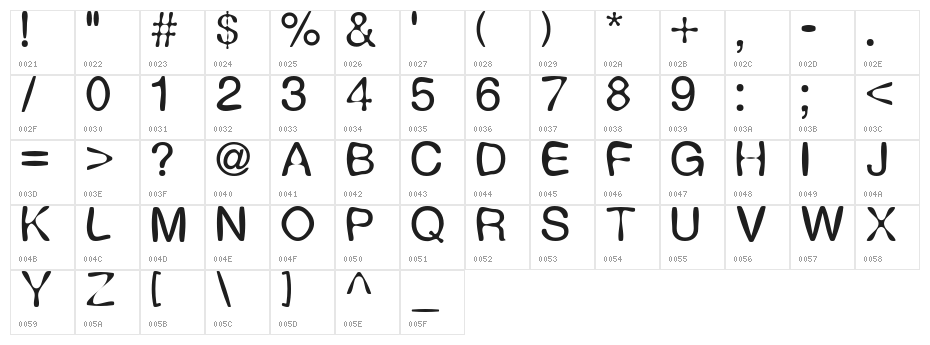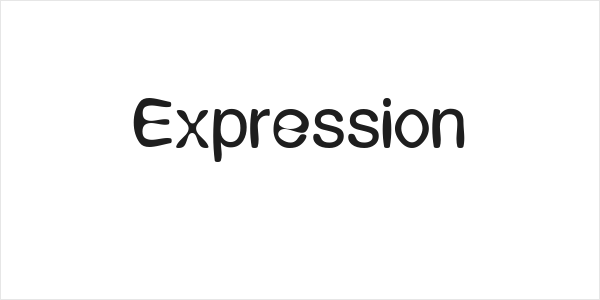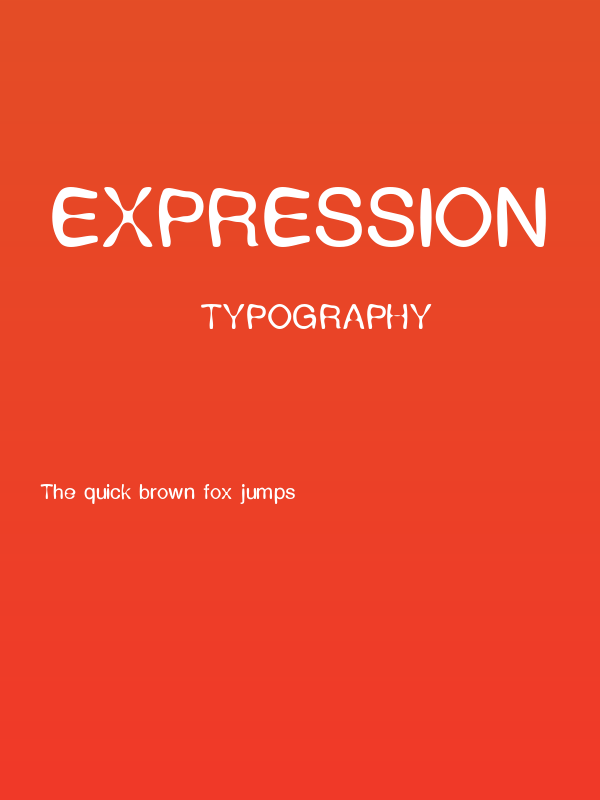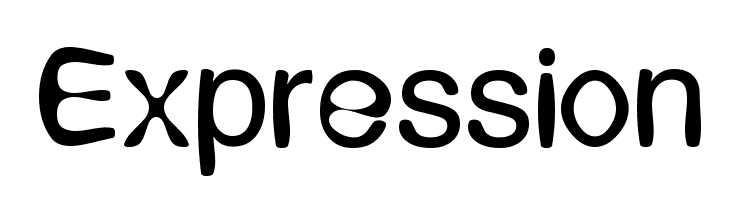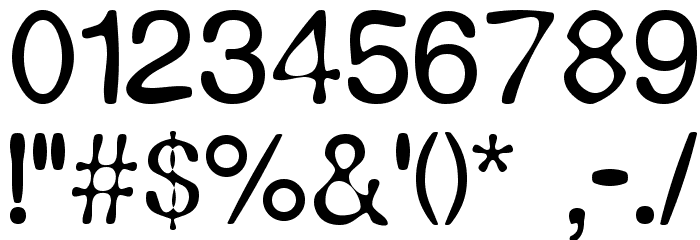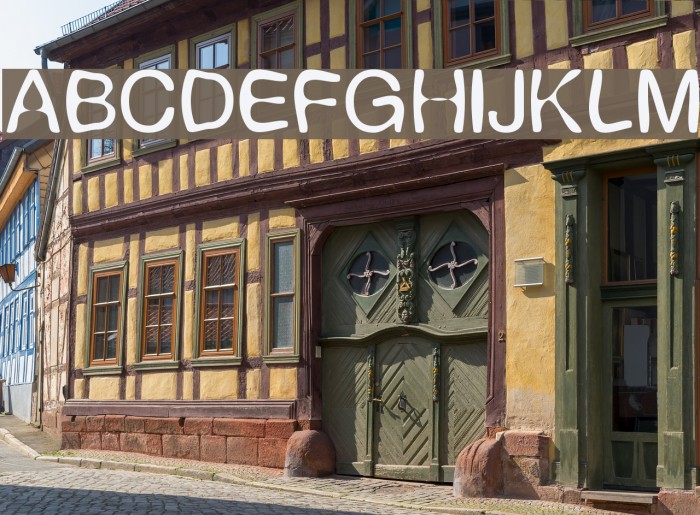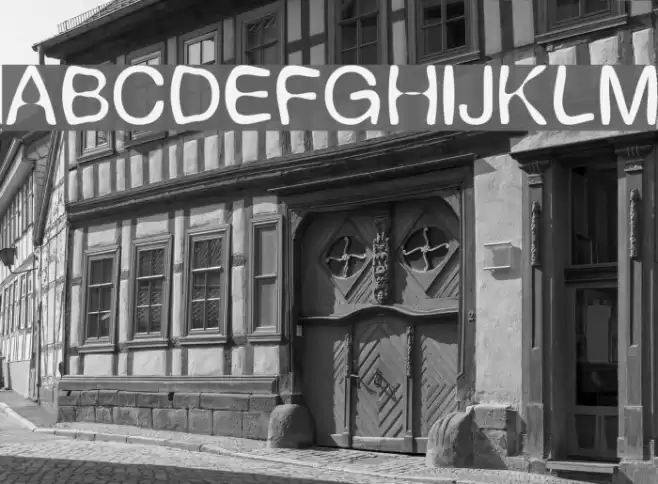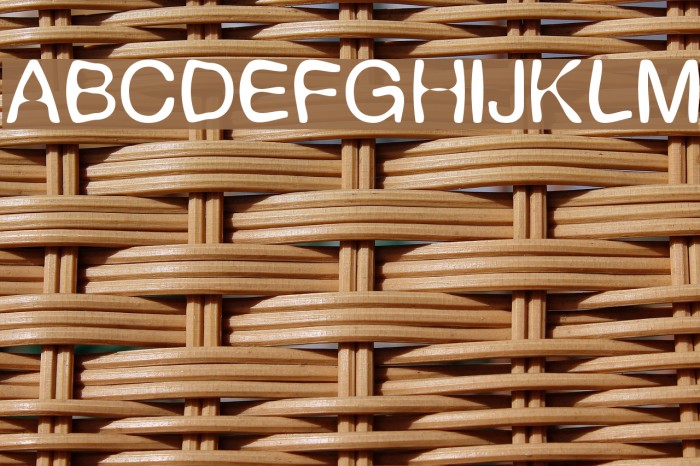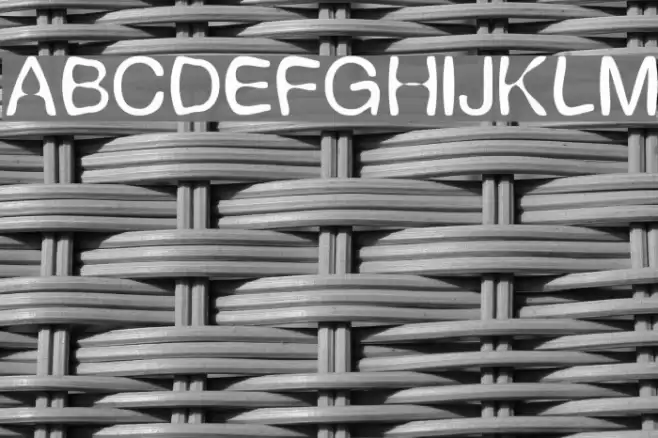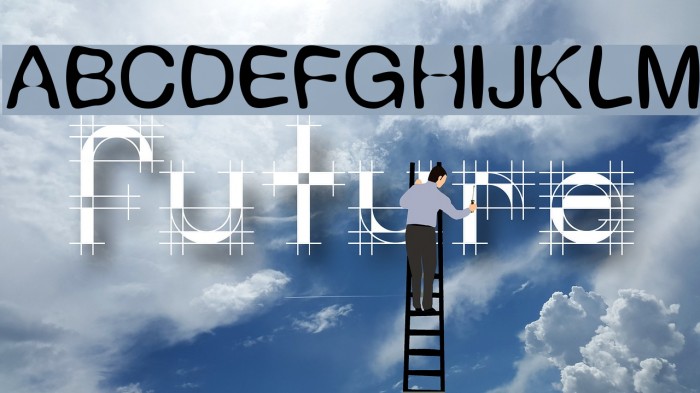
Expression Font
| Общий стиль | Playful, Whimsical |
| Рекомендуемые проекты | Ideal for children's books, playful branding, party invitations, and creative posters. |